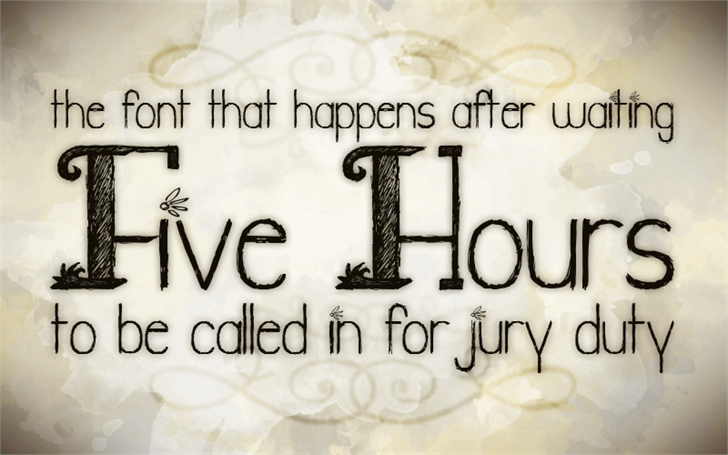
Jury Duty Font
A fonte ‘Jury Duty Font’, criada pelo designer Hamilton, é perfeita para quem procura uma graça leve e divertida no seu trabalho de design. Esta font tem um estilo descontraído e colorido que certamente será a cara de qualquer projeto em que você esteja trabalhando. Não importa se é para um site amigável ou um e-book educativo, sua aparência alegre pode torná-lo mais envolvente para o usuário. A fonte ‘Jury Duty Font’ está disponível gratuitamente para uso pessoal, mas para incorporá-la em algo comercial, é uma ótima ideia fazer uma pequena doação à designer. A fonte tem um design moderno e minimalista, combinando linhas elegantes com traços ligeiramente desequilibrados que dão a ela um toque irreverente. É perfeita para quando você quer dar vida aos seus projetos de maneira divertida e fresca. Para designers atentos à sua marca ou personalidade, esta fonte pode ser um grande diferencial. Ela não apenas traz uma graça única ao seu trabalho, mas também oferece uma opção gratuita que permite a criação de design incrível mesmo para iniciantes ou quem busca cortar gastos. Além disso, o uso da ‘Jury Duty Font’ em diferentes formatos pode torná-lo um recurso valioso. Pode ser usado para criar gráficos informativos, cartazes publicitários, e até mesmo materiais educacionais de forma divertida e inovadora. E com a opção de doação à designer, você ainda está contribuindo positivamente no desenvolvimento da arte digital.